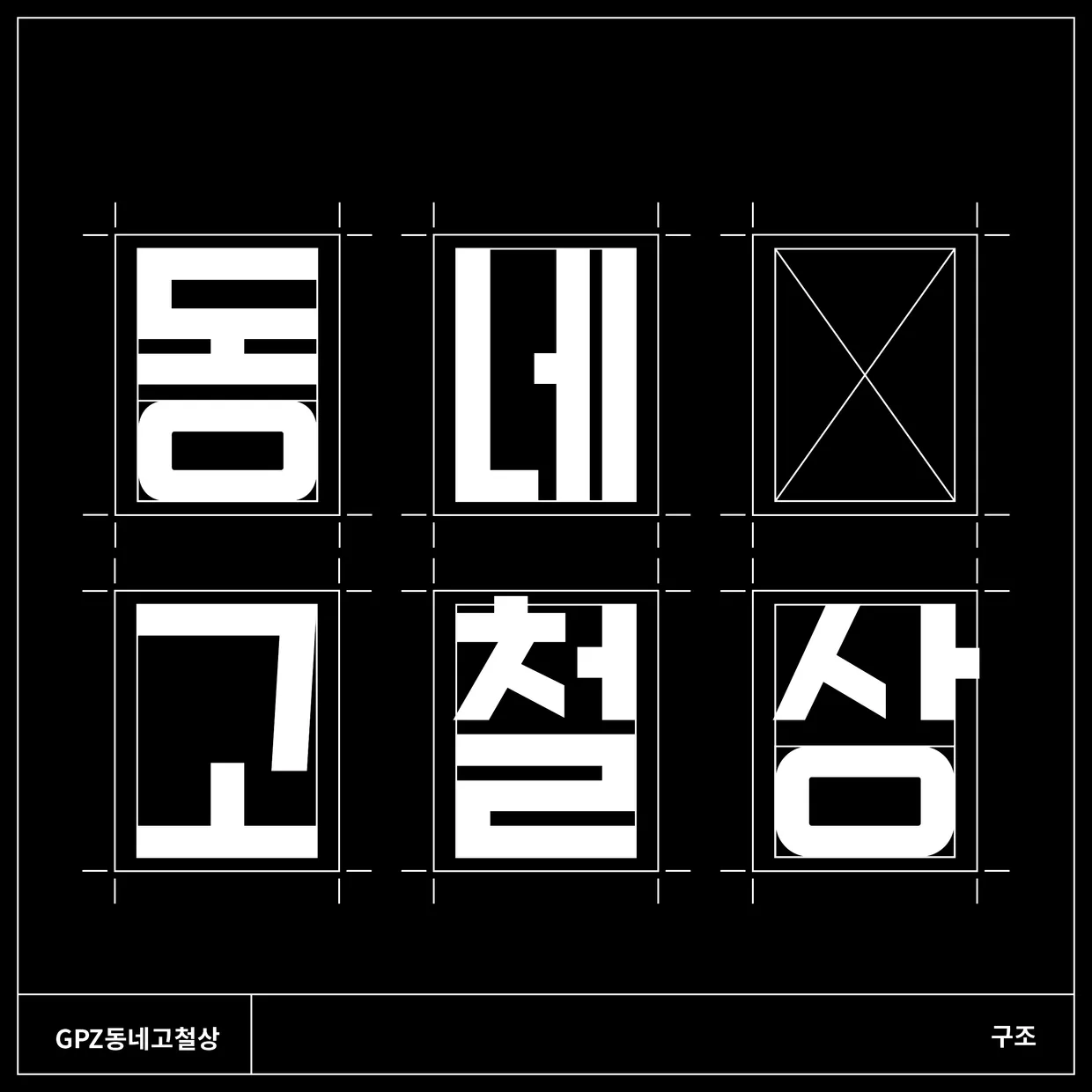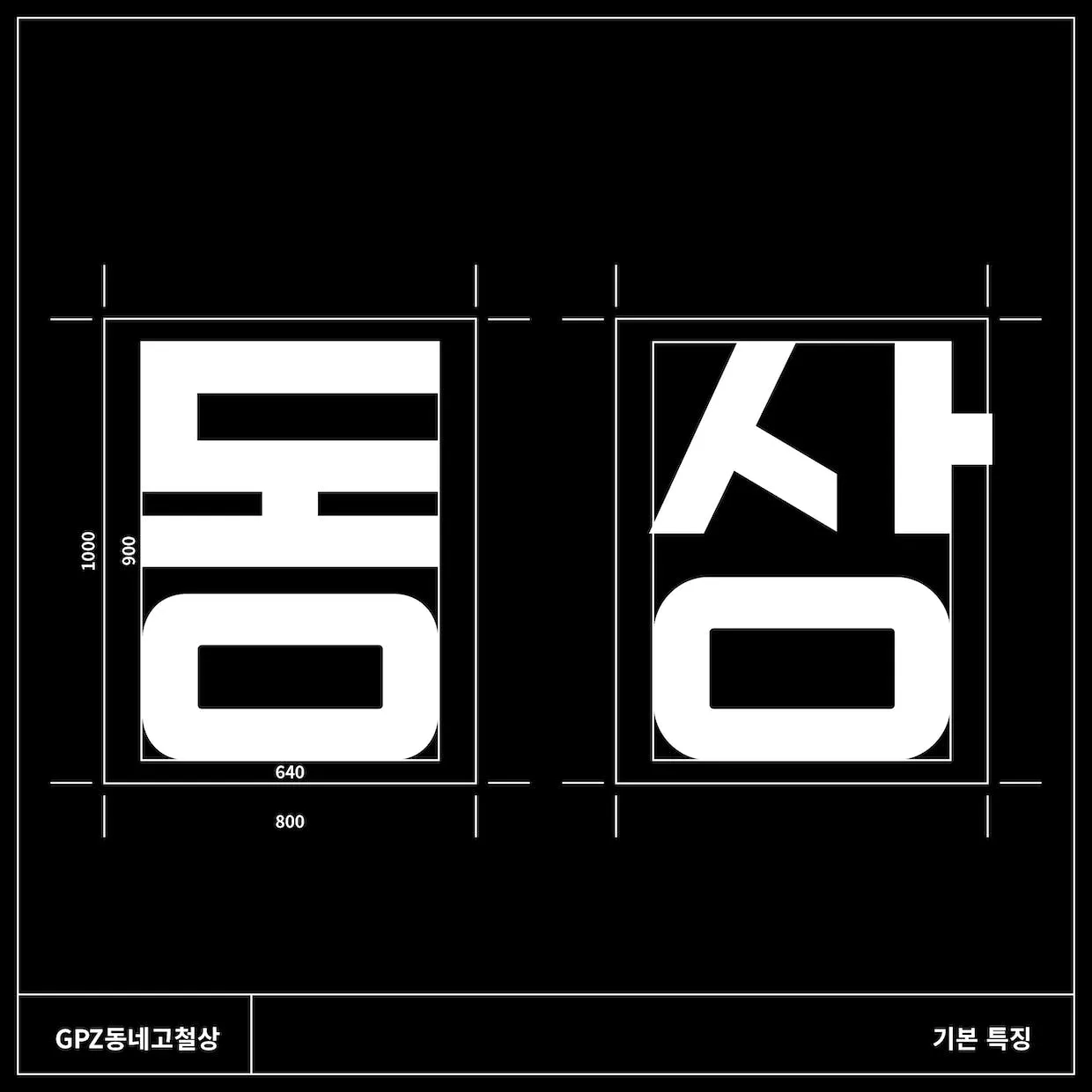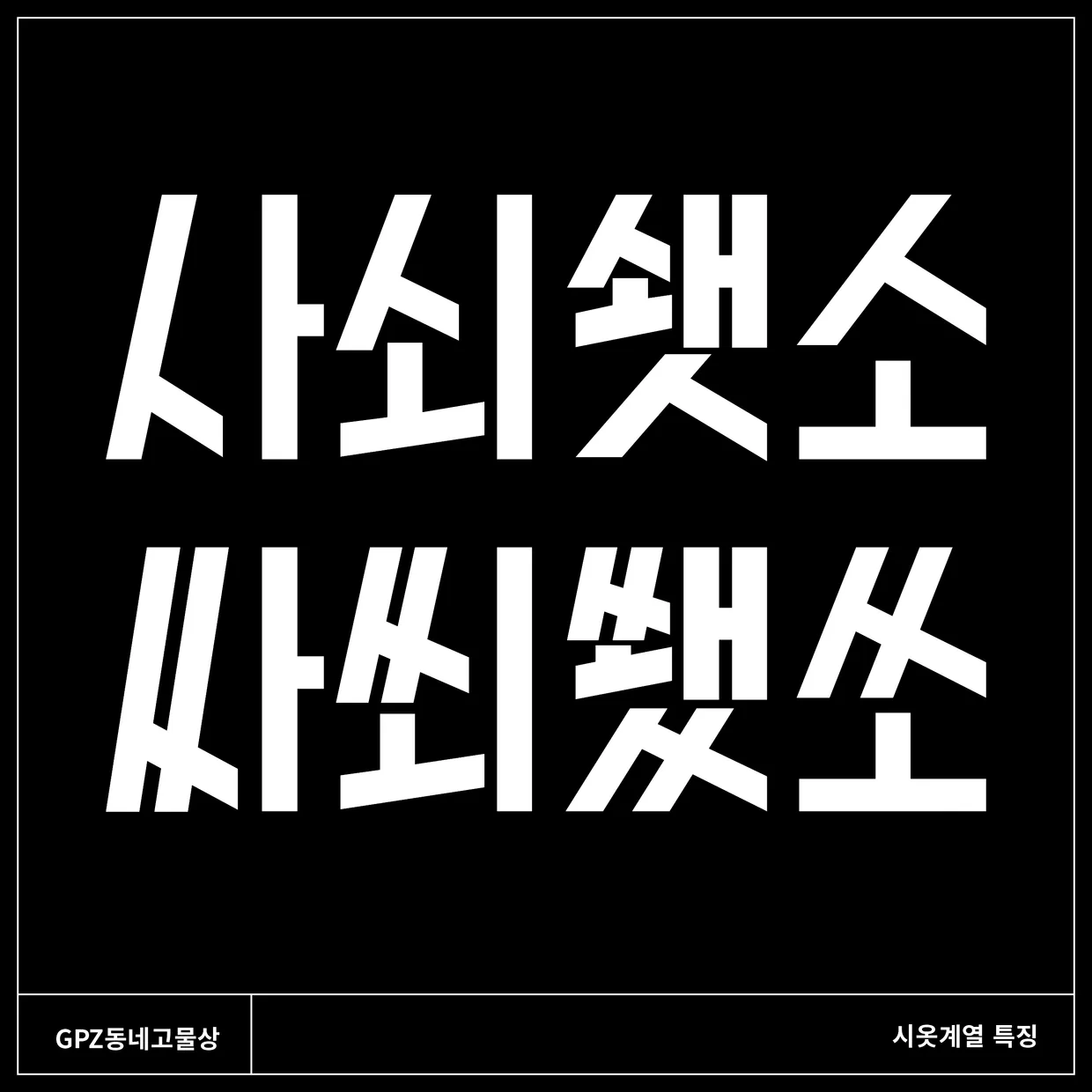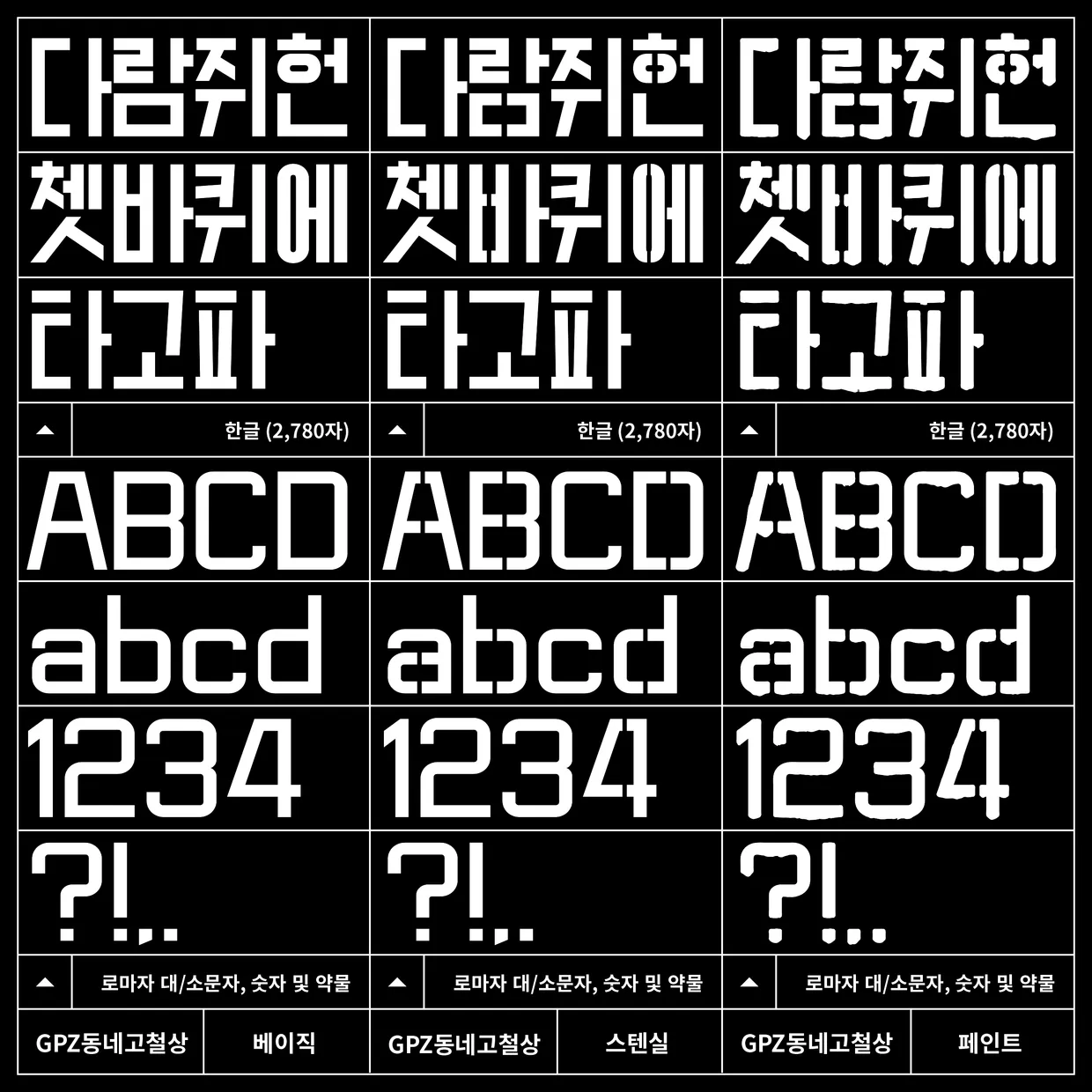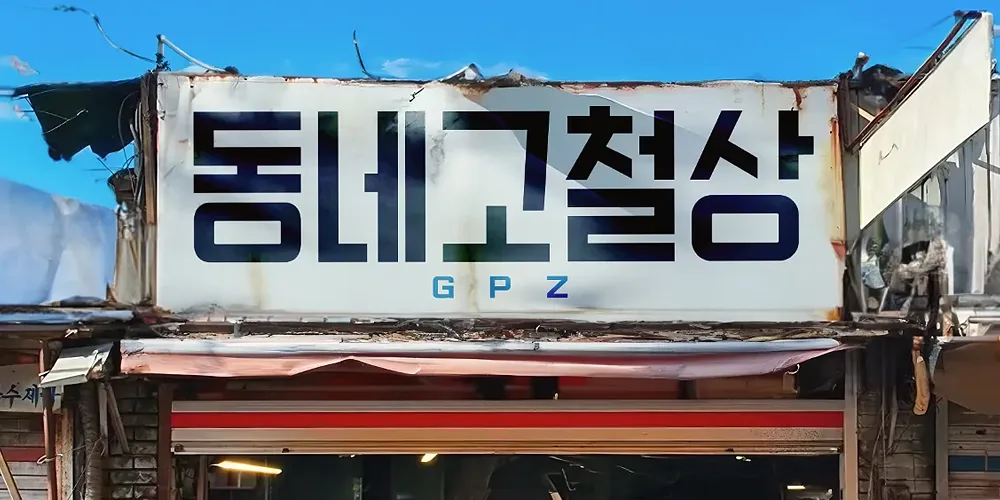
GPZ동네고철상
GPZ 동네고철상의 기본 구조
GPZ 동네고철상의 기본 특징
'GPZ 동네고철상'은 초성이 크게 그려진 고물상과 달리 종성이 크게 그려진 서체입니다. 이 때문에 고물상과는 다른 투박함을 보입니다. 옛날 학교 교재나 군사교본 등에서 보이던 형태로, 역시 복고적 인상을 더할 때나 주목도를 높이고 싶을 때, 독특한 미감을 주고자 할 때 적합할 것 같습니다.
GPZ 동네고철상의 자음 생김새
GPZ 동네고철상의 시옷계열 특징
'GPZ 동네고철상'의 색다른 특징은 시옷 계열의 생김새입니다. 갈래 시옷, 지읒이 뻗는 모습과는 다르게 앞쪽 다리를 뒤쪽 다리가 받치고 있는 듯한 모습이 눈에 띕니다. 마찬가지로 옛날 학교 교재나 군사교본 등에서 보인 독특한 형태로서 현재에는 잘 보이지 않지만 그대로 살려 시대적 인상을 더하고자 했습니다.
GPZ 동네고철상의 스타일
GPZ 동네 고철상의 스타일 상세 모습
'GPZ 동네고철상'은 한글 2,780자에 로마자 대/소문자를 포함하며 숫자와 약물 및 추가자로 구성됩니다. 고물상과 마찬가지로 스타일로는 '베이직', '스텐실'과 '페인트 총 3종이 있습니다.